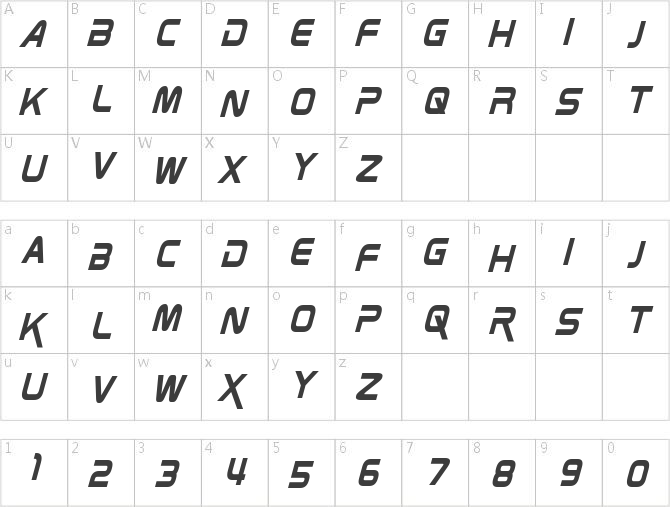
字體名稱: Zebulon
Zebulon Condensed Italic
Zebulon Condensed Italic介紹
Zebulon Condensed Italic字體字庫是一款讓人賞心悅目、百看不厭的英文字體,適合各類廣告和產品包裝設計應用,字體大小0.02MB,格式為ttf字體,上傳用戶是快霸中國,作者/版權方為未知